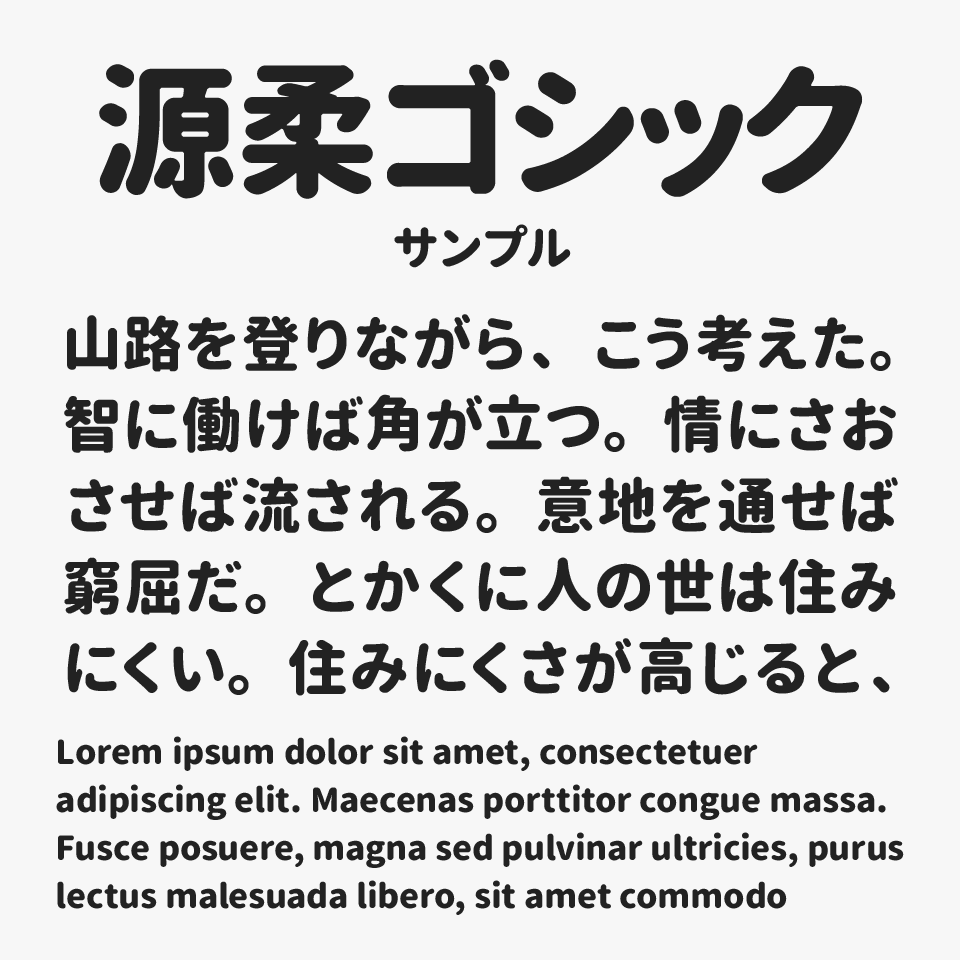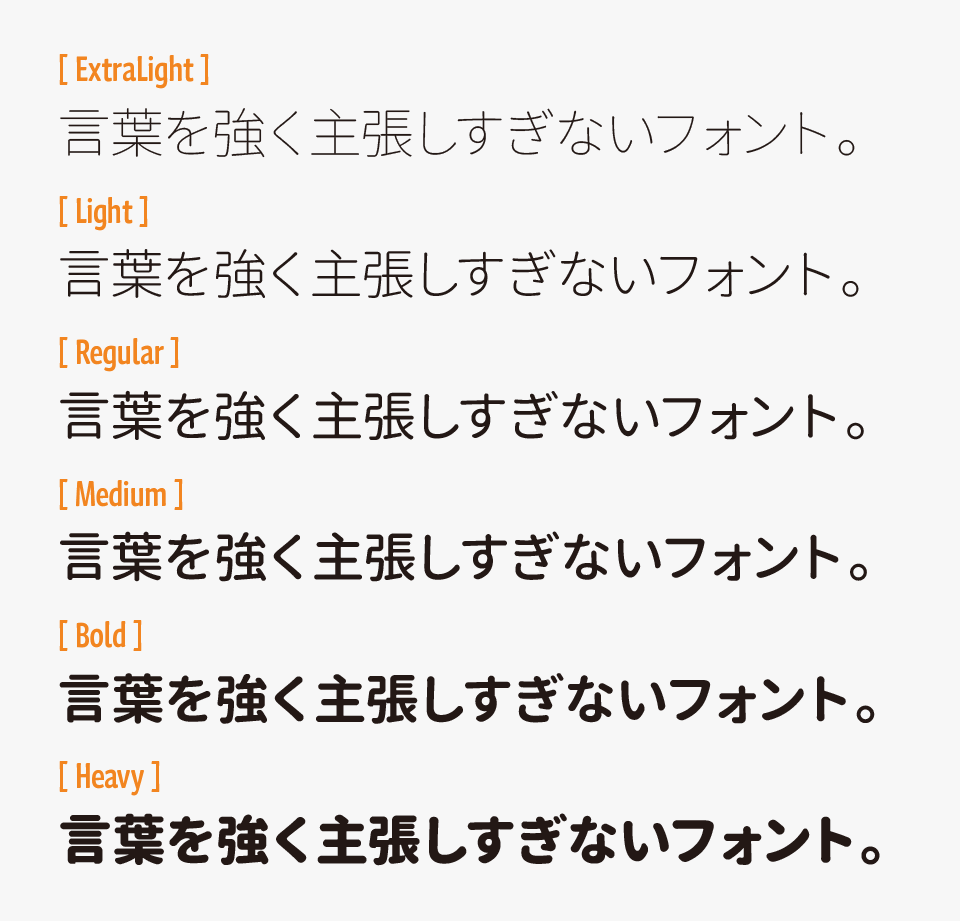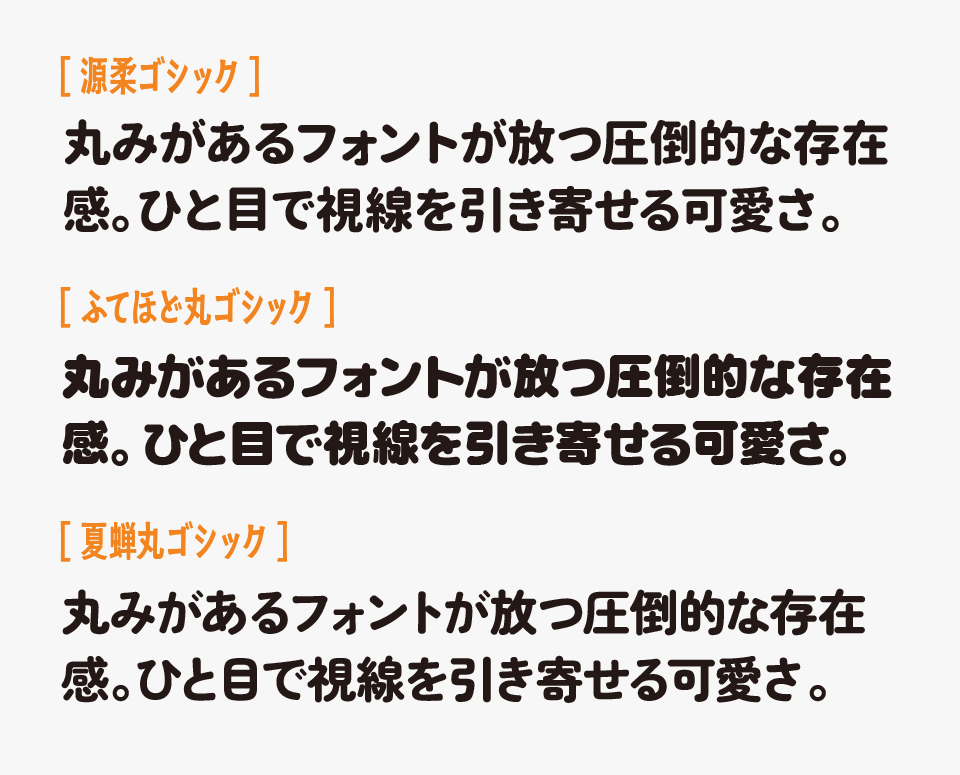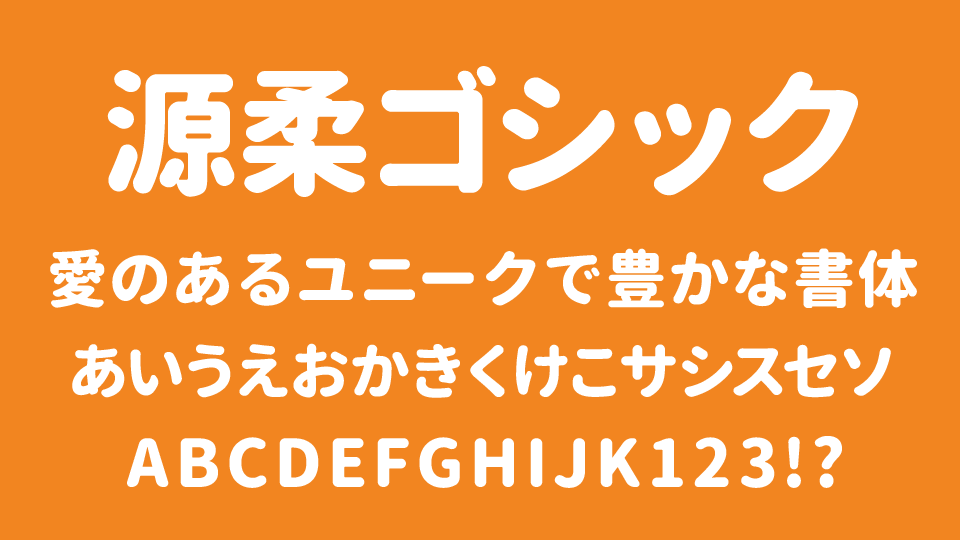
源柔ゴシック (げんじゅうゴシック)フォントは、源ノ角ゴシックをベースして、文字の角をやわらかく丸めて制作された丸ゴシック風フォントです。
源ノ角ゴシックならではの読みやすさや扱いやすさをしっかり受け継ぎながら、角を丸くすることで、やさしく温かみのある印象に仕上がっています。すっきりと整ったデザインなので、長文でも読みやすく、Webデザインや資料、動画テロップなど幅広いシーンで使いやすいフォントです。
また、ウェイトは6種類用意されており、さらに角丸の強さも「ひかえめ(L)・普通(Nomal)・強め(X)」の3タイプから選べるため、デザインの雰囲気に合わせて細かく調整できるところも魅力です。
かわいらしくしたい場面から、落ち着いたやわらかさを出したい場面まで、幅広く活用できるフォントとなっています。
ほかの丸ゴシックフォントと比較すると、源柔ゴシックは角丸の処理が控えめで、さりげない丸みが心地よいフォントとなっています。(比較フォントは、ふてほど丸ゴシック、夏蝉丸ゴシックと比べています。)
収録文字は、ひらがな・カタカナ・英数字・記号・日常で使用する漢字はカバーされています。